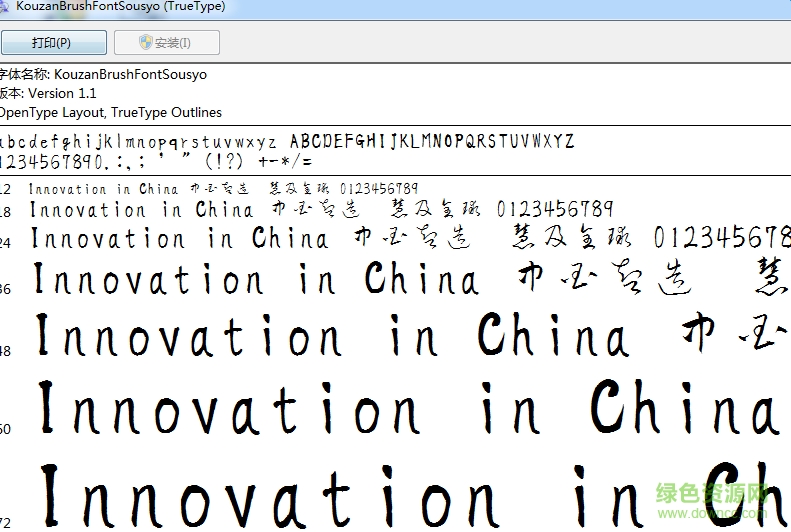
衡山毛筆草書體
衡山毛筆草書字體是一款極具個(gè)性的毛筆字體,改字體可以適用于書報(bào)刊標(biāo)題,廣告設(shè)計(jì)、印刷、商標(biāo)注冊(cè)、名稱、包裝等應(yīng)用,有喜歡的朋友可免費(fèi)下載收藏。
衡山毛筆草書字體是一款超好用的個(gè)性毛筆字體,改字體字跡非常飄逸,有喜歡的朋友可以來綠色資源網(wǎng)下載使用!